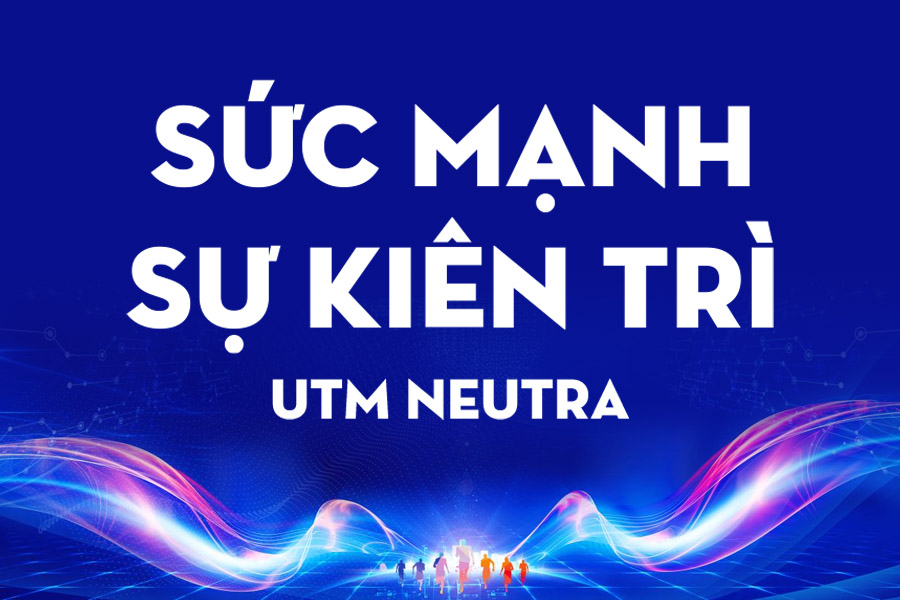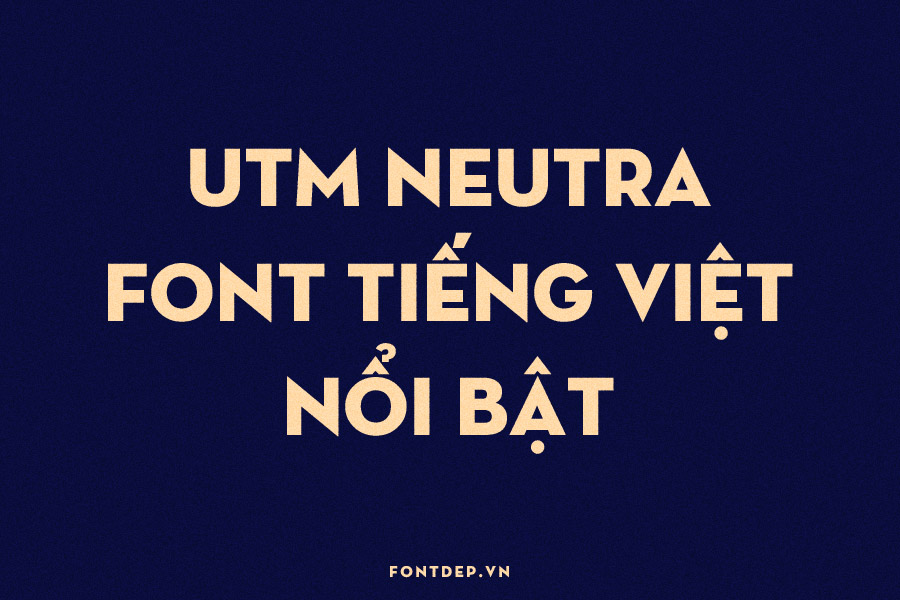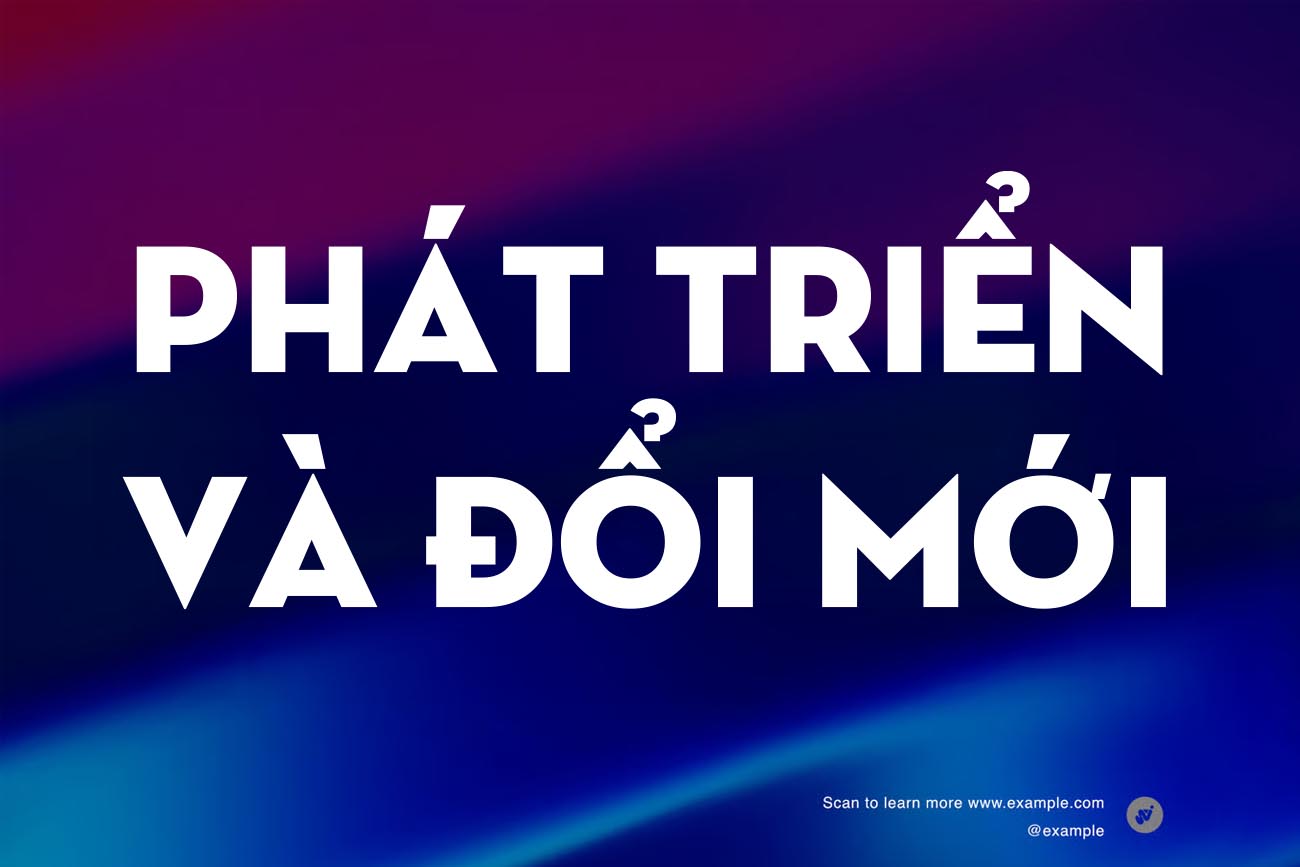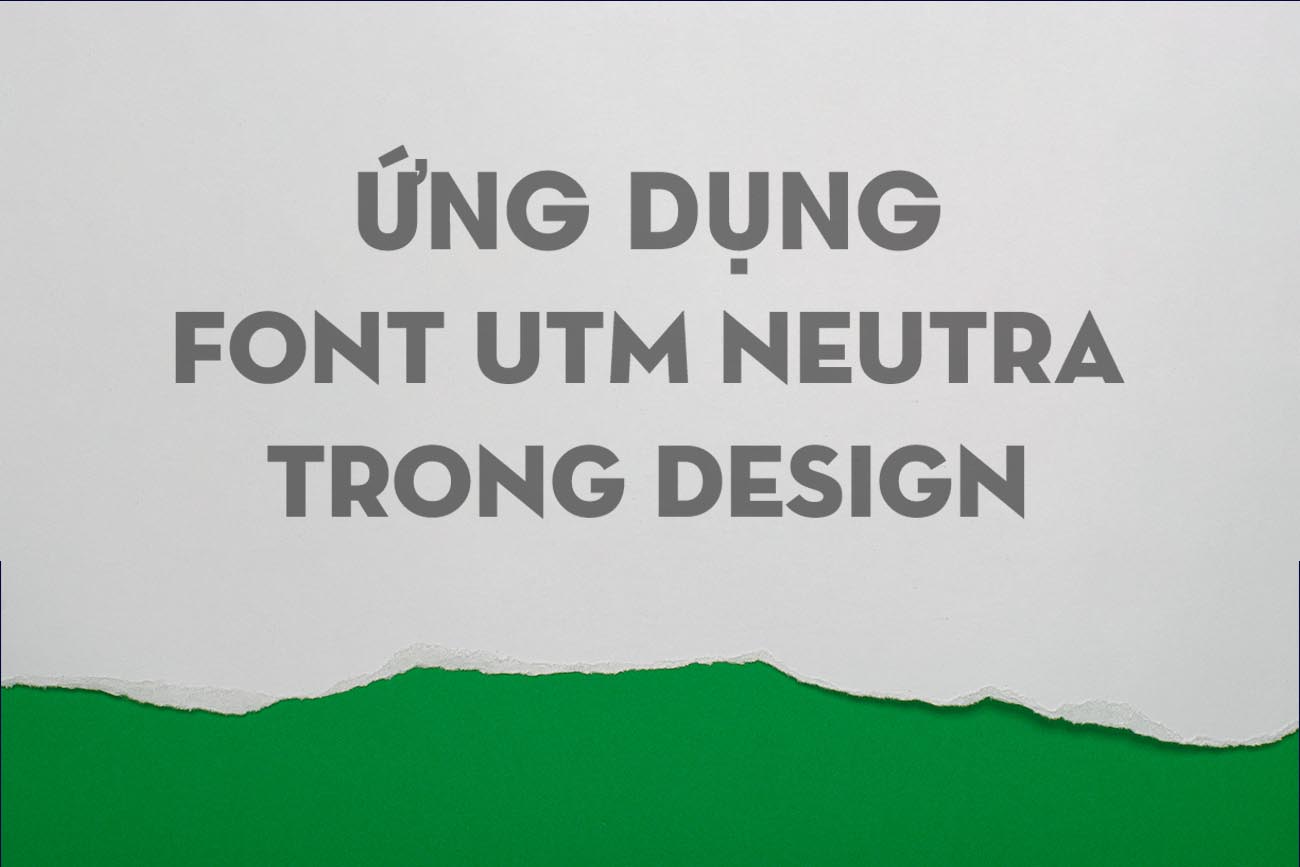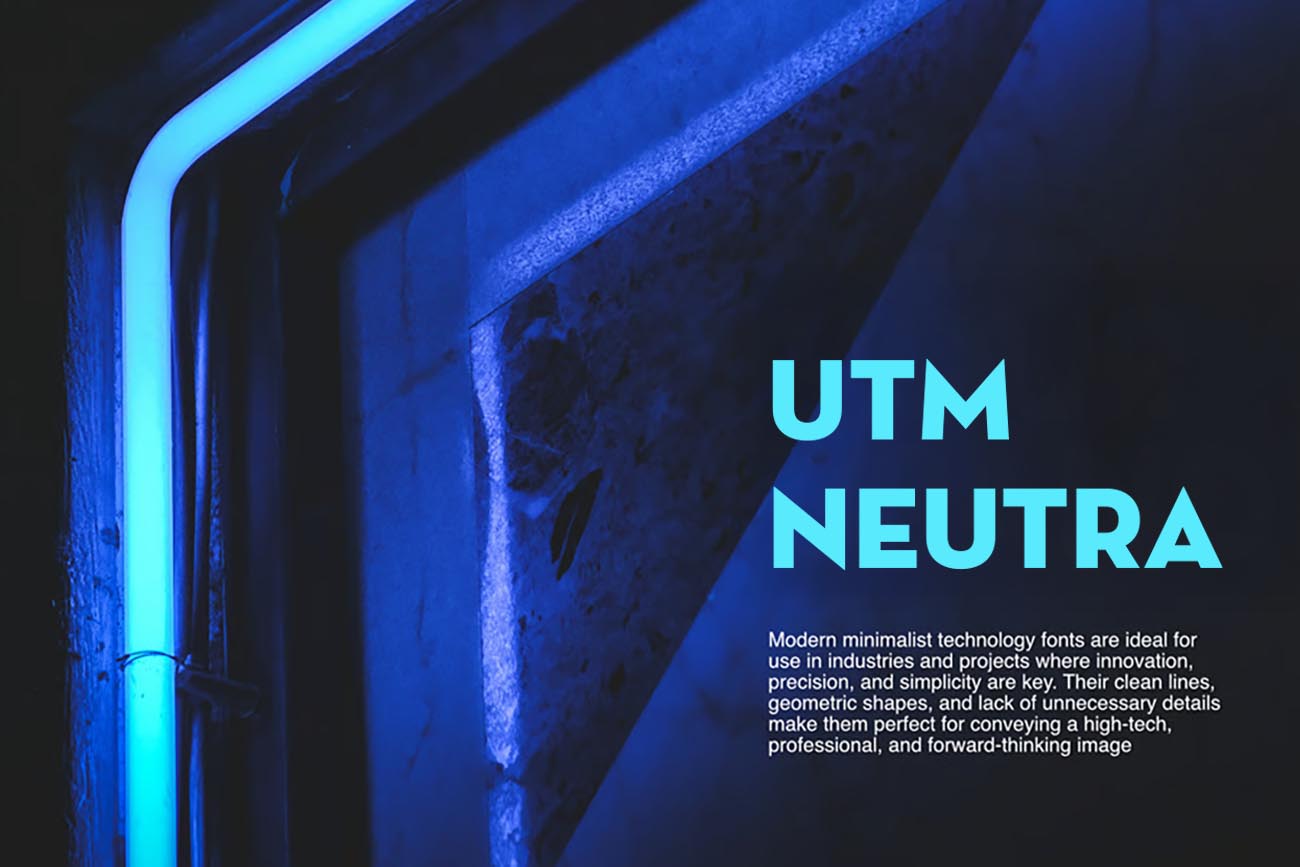
Phông chữ Việt hóa UTM Neutra chuẩn - Kiểu chữ cứng cáp cho thiết kế
Trong kho tàng typography quốc tế, Neutraface là một trong những font sans-serif kinh điển, được sáng tạo bởi Christian Schwartz và phát hành bởi House Industries vào năm 2002. Thiết kế này lấy cảm hứng từ công trình kiến trúc của Richard Neutra – kiến trúc sư nổi tiếng với phong cách hiện đại, tinh gọn và chú trọng hình khối.
Tại Việt Nam, bộ font này đã được nhóm UTM Việt hóa thành UTM Neutra, bổ sung đầy đủ dấu tiếng Việt và tối ưu hóa cho người dùng bản địa. Đây là bước hoàn thiện giúp Neutraface trở thành công cụ thiết kế gần gũi, dễ sử dụng trong nhiều dự án sáng tạo.
Đặc trưng nổi bật của font chữ UTM Neutra
Thiết kế hình học tinh gọn: Các ký tự mang cấu trúc rõ ràng, kết hợp hài hòa giữa đường cong tròn trịa và đường thẳng vững chắc.
Hiệu quả thị giác cao: Font có độ dày vừa phải, chữ in hoa nổi bật, dễ gây chú ý trong các tiêu đề lớn.
Hỗ trợ tiếng Việt đầy đủ: Phiên bản Việt hóa bởi UTM giúp người dùng thoải mái triển khai thiết kế mà không lo thiếu dấu hoặc lỗi ký tự.
Ứng dụng đa dạng: Phù hợp cho thương hiệu, poster, banner, website, tạp chí, slide thuyết trình hay các sản phẩm in ấn chuyên nghiệp.
Ưu điểm khi lựa chọn UTM Neutra
Không chỉ mang lại cảm giác tối giản và hiện đại, font chữ UTM Neutra Việt hóa còn có khả năng thích ứng linh hoạt. Bạn có thể sử dụng trong các dự án yêu cầu sự tinh tế, hoặc kết hợp màu sắc, hiệu ứng để tạo nên phong cách trẻ trung, cá tính.
Nếu bạn cần một font sans-serif Việt hóa vừa đẹp mắt, vừa tiện dụng, thì UTM Neutra chính là lựa chọn đáng giá. Sự kết hợp giữa thiết kế gốc từ Christian Schwartz và quá trình Việt hóa chỉn chu của UTM đã tạo nên bộ font mạnh mẽ, chuyên nghiệp và dễ ứng dụng trong mọi lĩnh vực thiết kế.